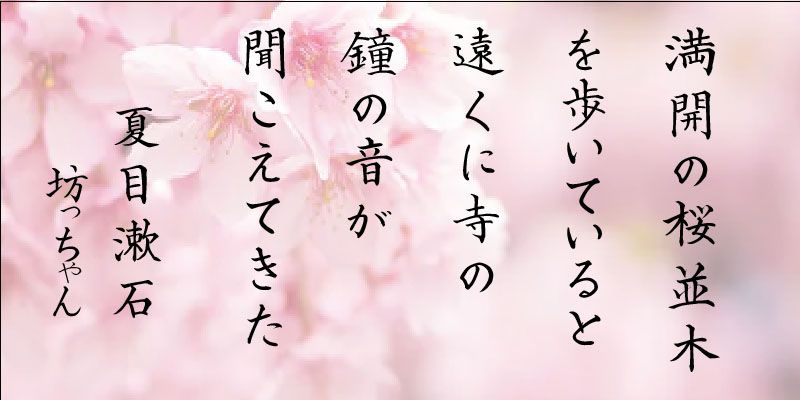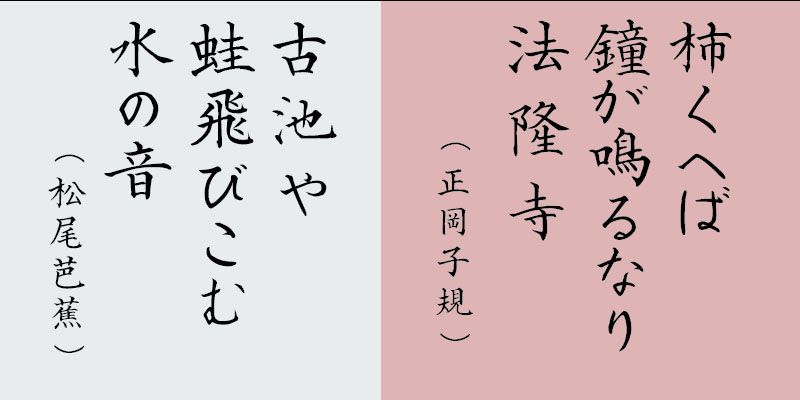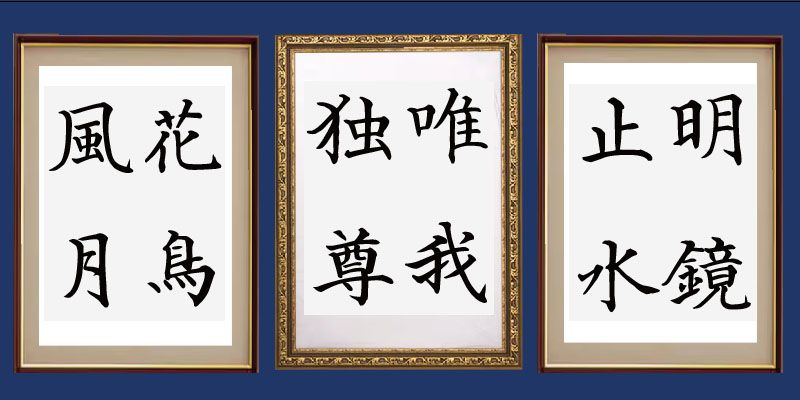
이 정사각형 스타일의 브러시 스크립트 서체는 굵고 가는 획 사이의 높은 대비, 길고 짧은 획의 조합, 미묘하게 다른 획 모양에 세심한 주의를 기울입니다. 글자 형태의 구조는 정렬된 문자 요소로 유려하게 표현됩니다.
이 서체의 각 글꼴에 포함된 영숫자, 히라가나 및 가타카나 문자는 각각 고유한 문자 너비를 가진 비례 글리프로 디자인되었습니다.
60년 이상의 캘리그래피 경력을 가진 Hakushu Nakamoto는 예쁘고 능숙한 필기체를 사용하여 브러시 스크립트 글꼴을 제작했습니다. 그는 전문 캘리그래퍼로서 작업하면서 클라이언트의 다양한 요구에 맞게 맞춤형 서비스를 제공하고 있습니다. Nakamoto 디자인을 사용하면 전통 캘리그래피 기술을 더 잘 이해할 수 있습니다.